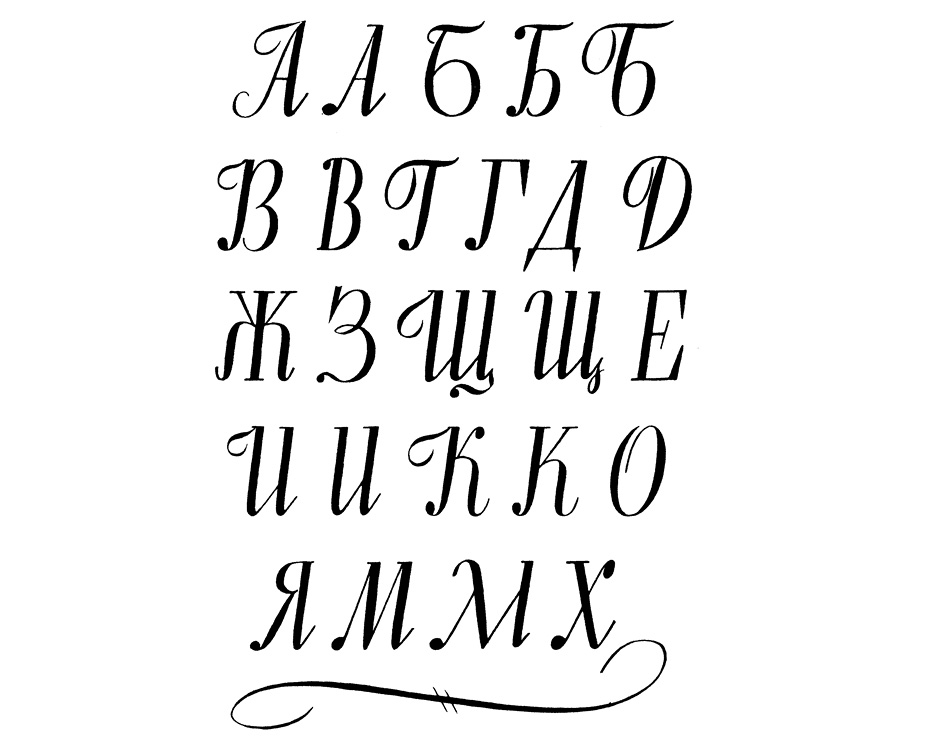
α — Греческая строчная буква альфа: U+03B1 alpha
Значение символа
Греческая строчная буква альфа. Греческое и коптское письмо.
Символ «Греческая строчная буква альфа» был утвержден как часть Юникода версии 1.1 в 1993 г.
Похожие символы
я — Кириллическая строчная буква я: U+044F
Значение символа
Кириллица.Символ «Кириллическая строчная буква я» был утвержден как часть Юникода версии 1.1 в 1993 г.
τ — Греческая строчная буква тау: U+03C4 tau
Значение символа
Греческое и коптское письмо.Символ «Греческая строчная буква тау» был утвержден как часть Юникода версии 1.1 в 1993 г.
Похожие символы
Ø — Латинская заглавная буква O со штрихом: U+00D8 Oslash
Значение символа
Латинская заглавная буква O со штрихом. Дополнение к латинице — 1.
Символ «Латинская заглавная буква O со штрихом» был утвержден как часть Юникода версии 1.1 в 1993 г.
Красивые буквы для ника – украшаем имена и слова.
(Обновление: Июль 2020). Подборка знаков, красивых букв и символов для ников. Девочки и мальчики часто стараются оформить свой ник в Вконтакте, Одноклассниках, Аватарии вот такими красивыми буквами (пример ника: ❆Ŝĩƀℒίķě.ℛự), чтоб не искать эти буквы в интернете, собрал большинство из них на одной странице.
Английские буквы – латиница (символьный алфавит)
А – Ꭿ 凡 Ꮨ ₳ Ǻ ǻ α ά Ά ẫ Ắ ắ Ằ ằ ẳ Ẵ ẵ Ä Ą ą ǻ å â ã ā Λ λ Α ẫ ª â Ã Æ ä Ắ Ā ā ắ Å à Ά ά Ä Ằ Ǻ ǻ Λ ă ằ À â á Á ẳ Ą а ǽ ?
๖ۣۣۜB – ℬ Ᏸ β ฿ ß Ђ ᗷ ᗸ ᗹ ᗽ ᗾ ᗿ Ɓ ƀ ხ 方 ␢ Ꮄ ?️
๖ۣۣۜC – ☾ ℭ ℂ Ç ¢ ç Č ċ Ċ ĉ ς Ĉ ć Ć č Ḉ ḉ ⊂ Ꮸ ₡ ¢ Ç ĉ ć ς Ḉ č ċ € Ç Ć ¢ ć ç ς Ĉ с ĉ Ċ © ċכ Č ?
๖ۣۣۜD – ᗫ Ɗ Ď ď Đ đ ð ∂ ₫ ȡ ?
๖ۣۣۜE – ℯ ໂ ६ £ Ē ℮ ē Ė ė Ę ě Ě ę Έ ê ξ Ê È € É ∑ Ế Ề Ể Ễ é è ع Є є έ ε ?
๖ۣۣۜF – ℱ ₣ ƒ ∮ Ḟ ḟ ჶ ᶂ φ ?
๖ۣۣۜG – Ꮹ Ꮆ ℊ Ǥ ǥ Ĝ ĝ Ğ ğ Ġ ġ Ģ ģ פ ᶃ ₲ ?
๖ۣۣۜH – ℍ ℋ ℎ ℌ ℏ ዙ Ꮵ Ĥ Ħ ħ Ή ♅ 廾 Ћ ђ Ḩ Һ ḩ ң ?
๖ۣۣۜI – ℐ ℑ ί ι Ï Ί Î ì Ì í Í î ϊ ΐ Ĩ ĩ Ī ī Ĭ ĭ İ į Į Ꭵ ?
๖ۣۣۜJ – ჟ Ĵ ĵ ᶖ ɉ ?
๖ۣۣۜK – ₭ Ꮶ Ќ k ќ ķ Ķ Ҝ ҝ ﻸ ᶄ ?
๖ۣۣۜL – ℒ ℓ Ŀ ŀ £ Ĺ ĺ Ļ ļ λ ₤ Ł ł ľ Ľ Ḽ ḽ ȴ Ꮭ £ Ꮑ Λ ?
๖ۣۣۜM – ℳ ʍ ᶆ Ḿ ḿ ♍ ᗰ ᙢ 爪 ♏ ₥ ?
๖ۣۣۜN – ℕ η ñ ח Ñ ή ŋ Ŋ Ń ń Ņ ņ Ň ň ʼn ȵ ℵ ₦ ?
๖ۣۣۜO – ℴ ტ ٥ Ό ó ό σ ǿ Ǿ Θ ò Ó Ò Ô ô Ö ö Õ õ ờ ớ ọ Ọ ợ Ợ ø Ø Ό Ở Ờ Ớ Ổ ổ Ợ Ō ō ?️
๖ۣۣۜP – ℙ ℘ þ Þ ρ Ꭾ Ꮅ 尸 Ҏ ҏ ᶈ ₱ ☧ ᖘ ק ァ ?
๖ۣۣۜQ – ℚ q Q ᶐ Ǭ ǭ ჹ ?
๖ۣۣۜR – ℝ ℜ ℛ ℟ ჩ ᖇ ř Ř ŗ Ŗ ŕ Ŕ ᶉ Ꮢ 尺 ?
шрифтов Bullet Journal (14 шрифтов для Bullet Journal, которые вам нужно попробовать!)
Простые шрифты для пулевого журнала
Ищете шрифтов для пулевого журнала , чтобы украсить свой журнал и улучшить свой почерк? Ознакомьтесь с этими замечательными шрифтами для журнала bullet journal, которые вы можете попробовать сегодня!
Хотя исходная система Bullet Journal задумывалась как минималистичная и чистая, многие пулевые журналисты — такие как я — обнаружили, что они могут использовать свой журнал также как инструмент для стимулирования творчества .